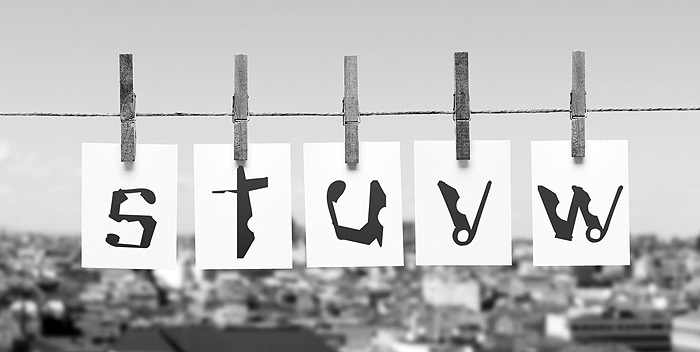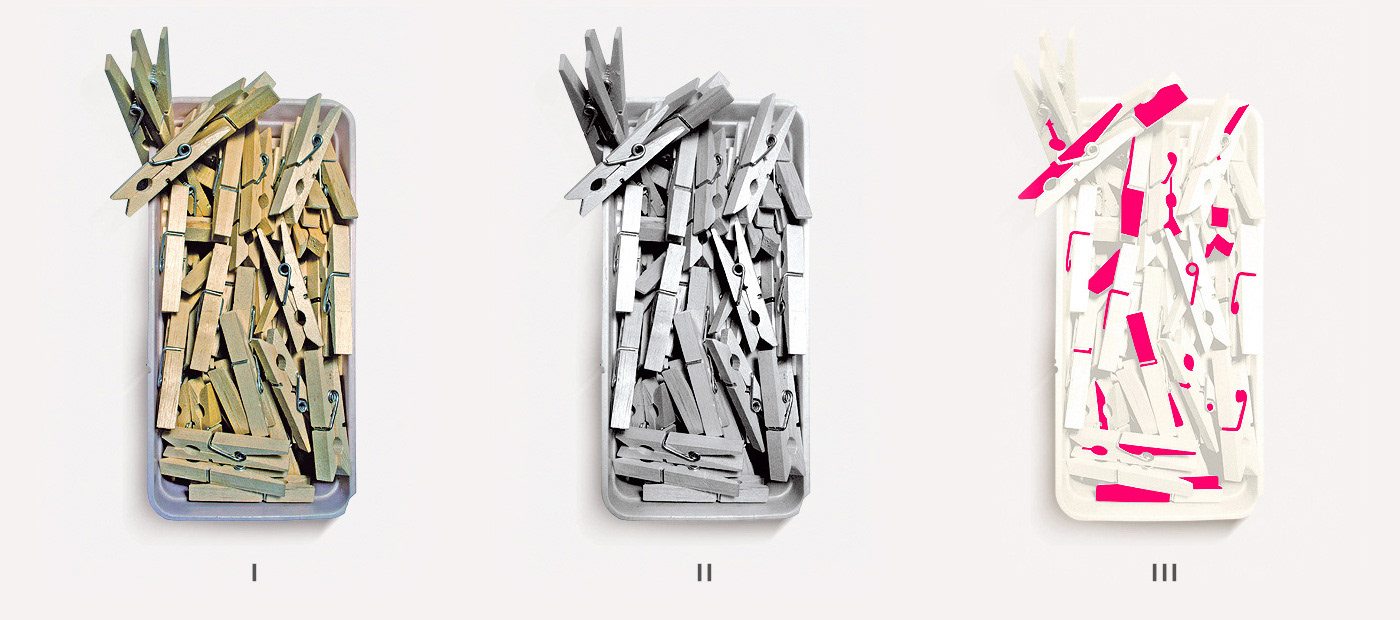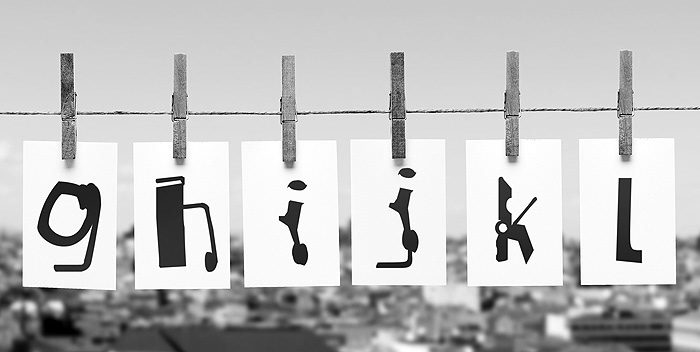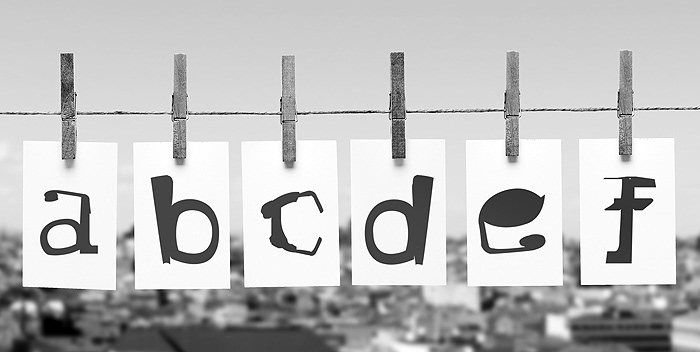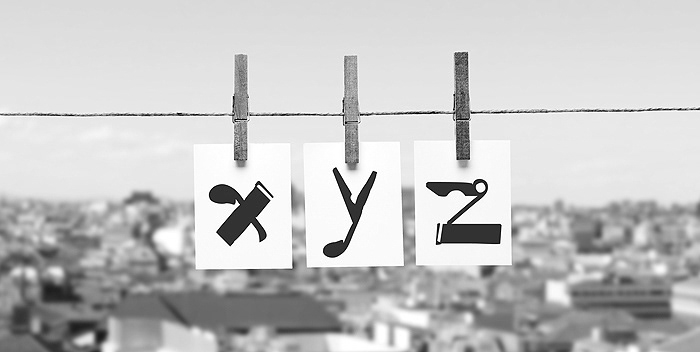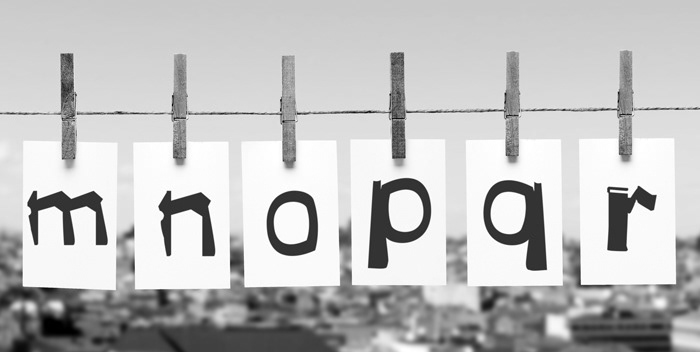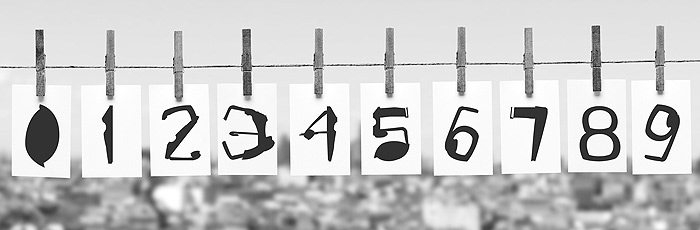
CLOTHEsPIN FREE FONT
La revista NEO2 Magazine sacó como tipografía del mes este experimento en el que se quería demostrar que si se mira con atención, en cualquier lugar hay elementos con los que crear algo de la nada, como por ejemplo una tipografía.